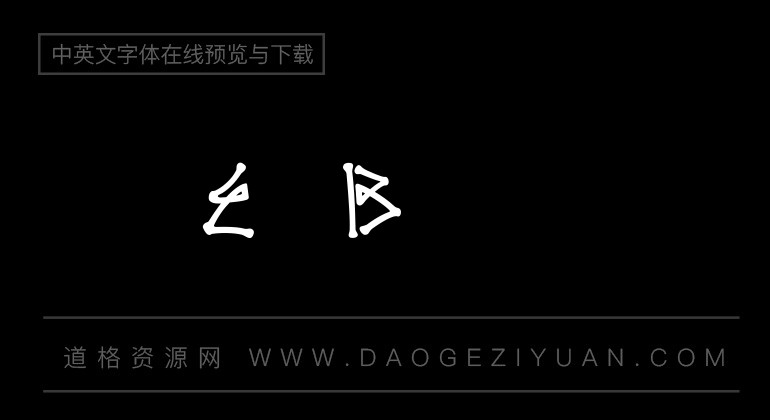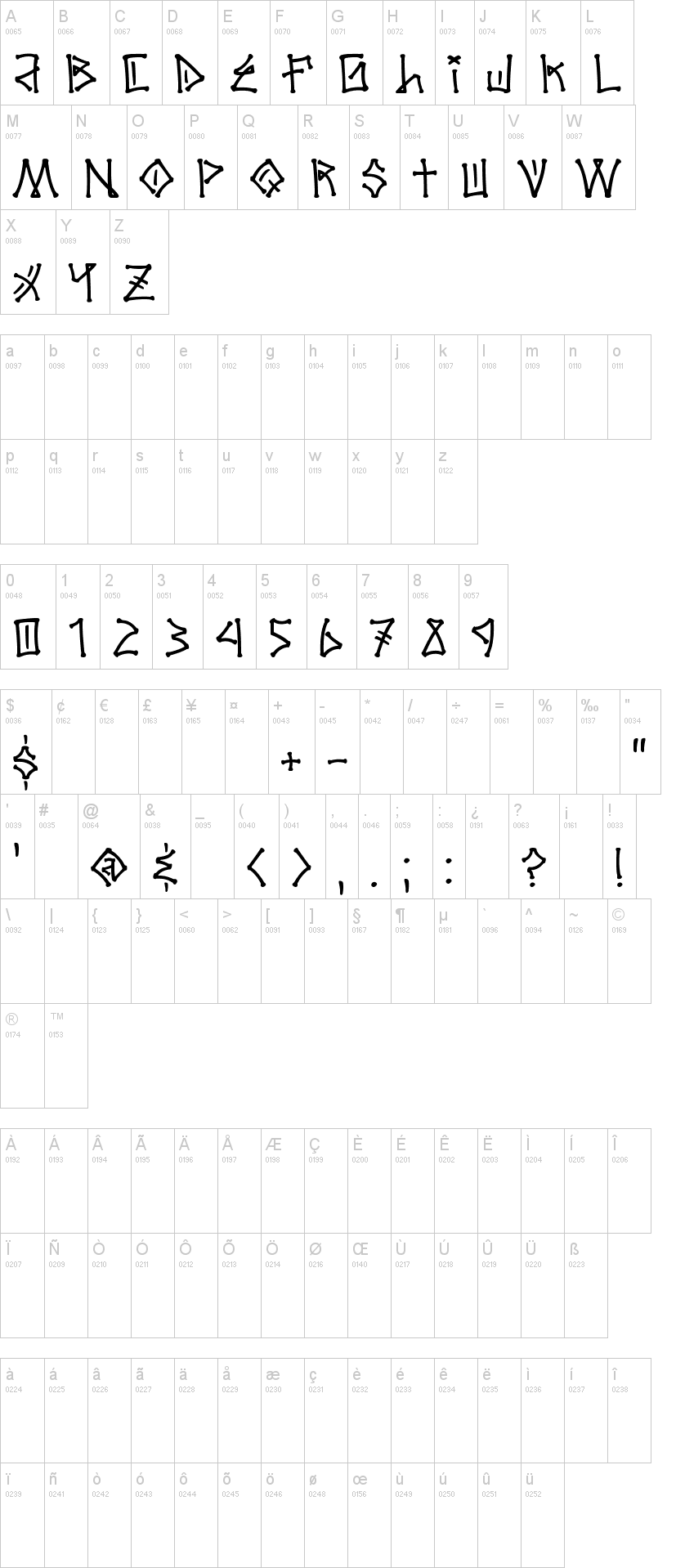
El Barrio字体是一款由Miguel Hernandez创作的拉丁文字体。它受到了西班牙和拉丁美洲文化的启发,具有独特的西班牙风格。它拥有粗细不一的线条,有助于提升文本的可读性和可视性。它的设计灵感来自于西班牙文化,具有活力和温暖的色调,可以为您的设计带来活力和温暖的氛围。内容介绍
El Barrio是一款非常不错的手写艺术字体,具有很好的视觉感,适合于文化类的宣传设计、商业类品牌的广告和产品包装设计以及个性化文字排版等较多场景。